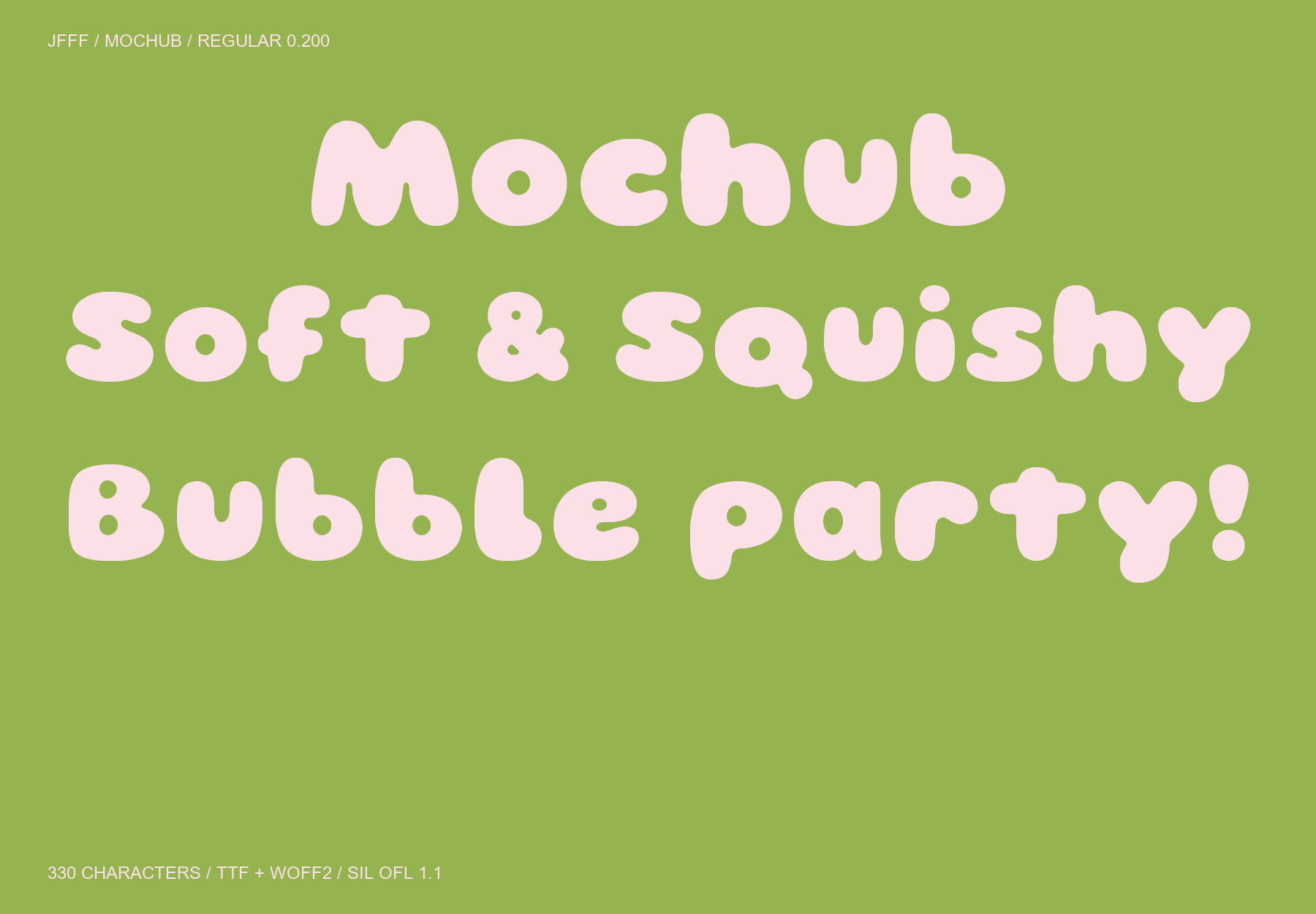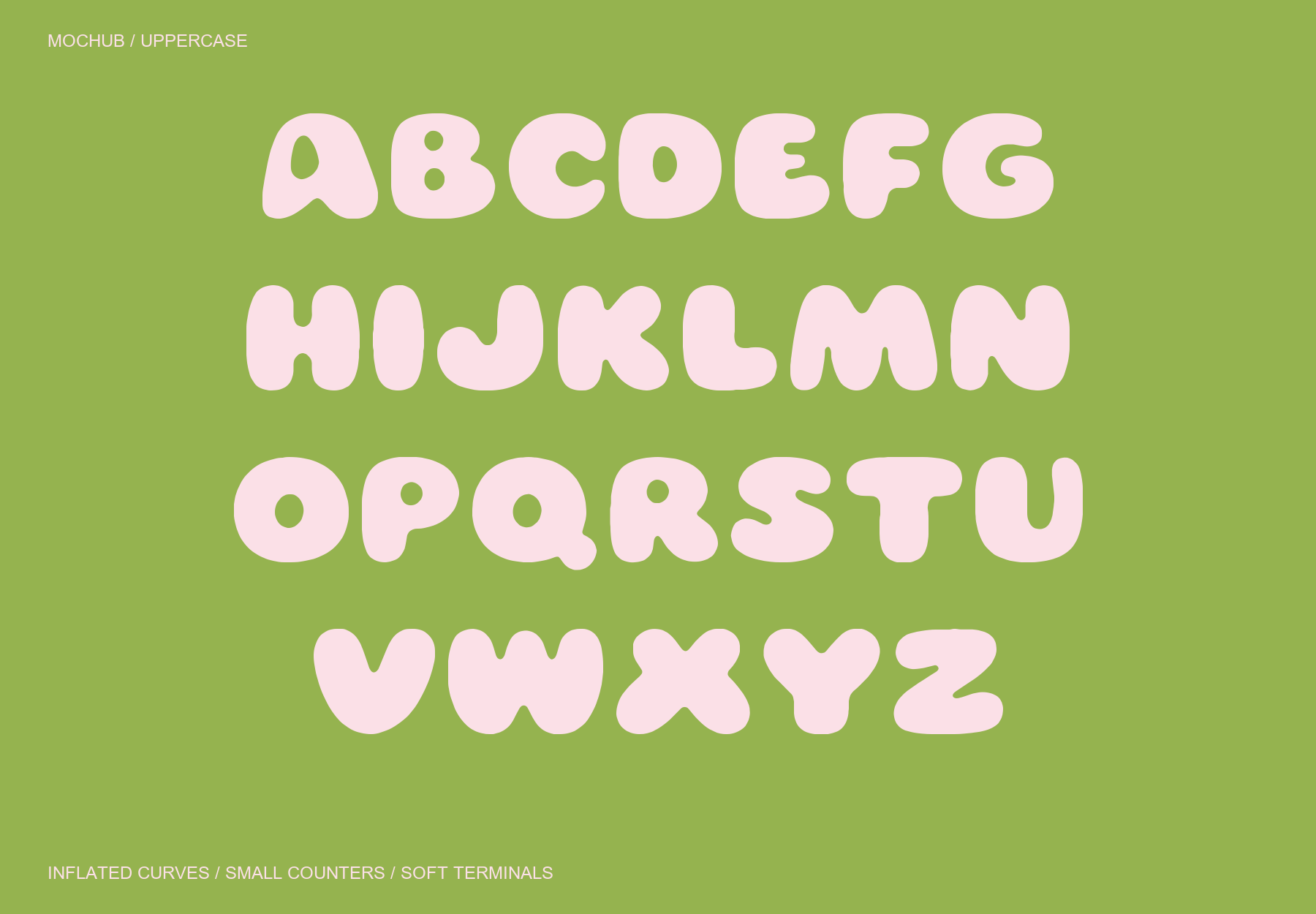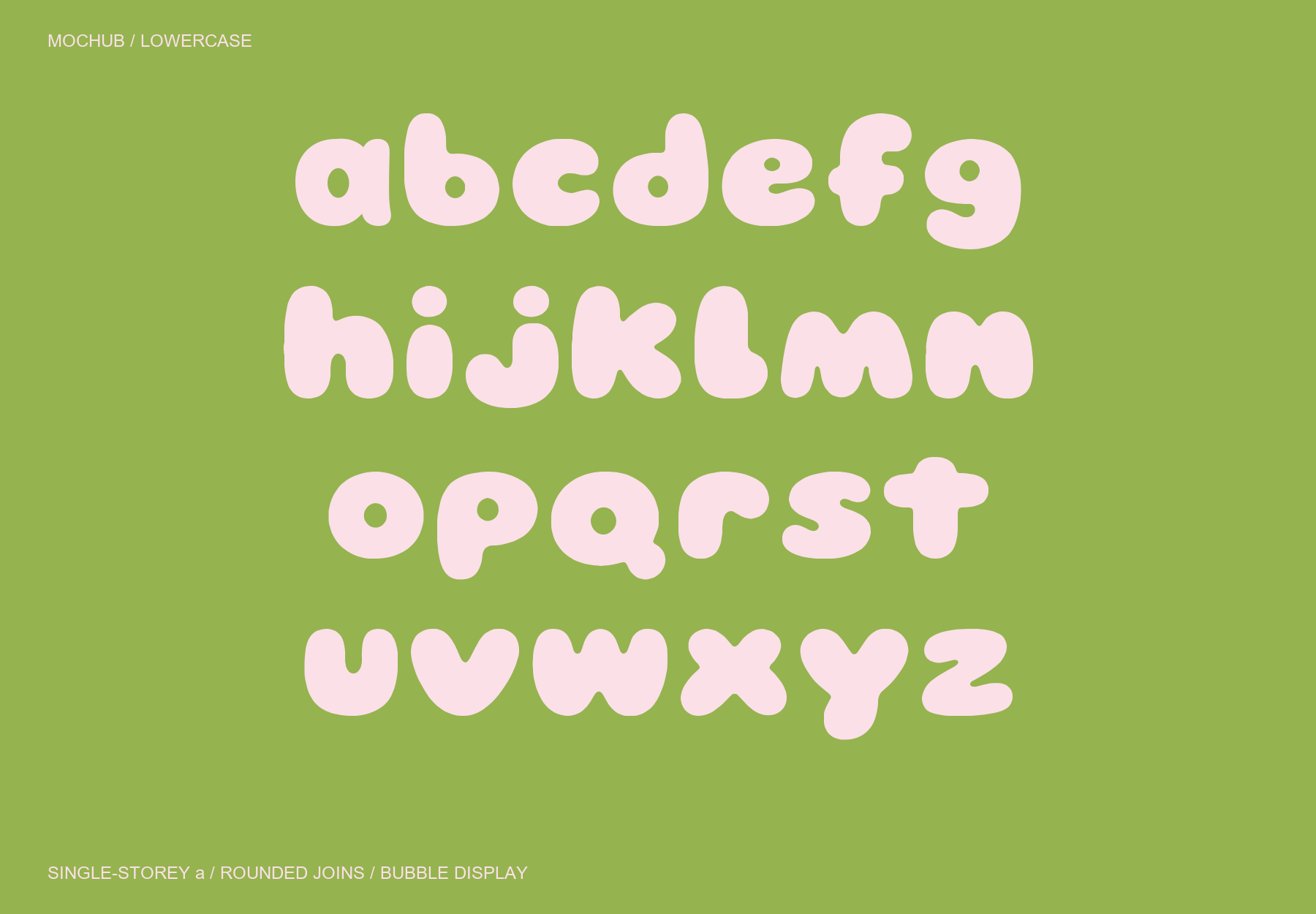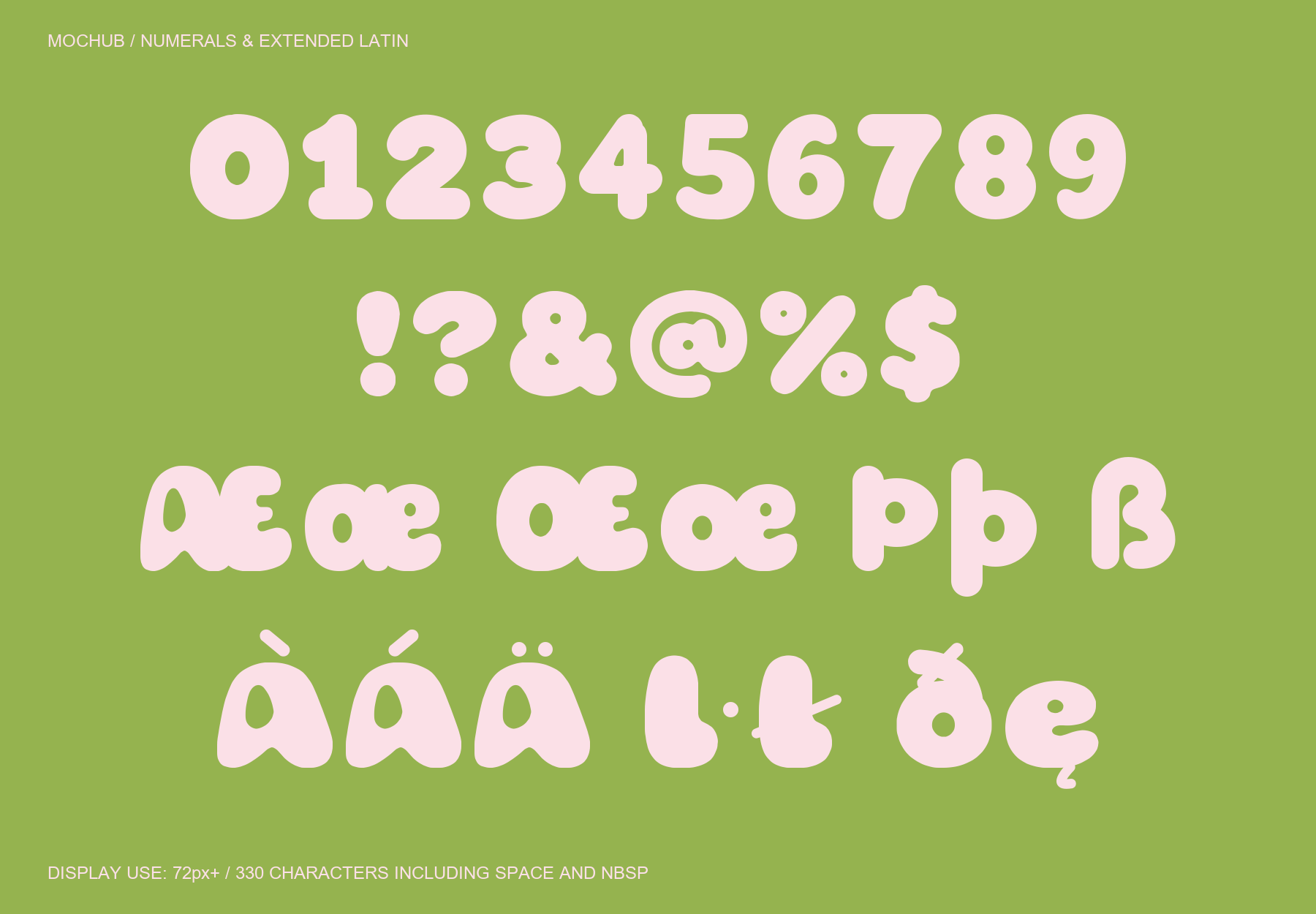
Mochub은 풍선처럼 부푼 획, 작은 속공간과 말랑하게 파인 연결부가 특징인 둥근 디스플레이 서체입니다. 소문자 a는 둥근 몸통과 짧은 오른쪽 기둥을 연결한 단층 구조로 설계했습니다. Regular 0.200 · 라틴 330자(공백·NBSP 2자 포함). 영문 대소문자, 숫자, 확장 라틴 악센트와 기호를 지원합니다. 한글은 포함하지 않으며 악센트는 완성형 문자로 지원합니다. TTF와 WOFF2를 하나의 ZIP으로 제공하고 SIL Open Font License 1.1로 무료 배포합니다. 72px 이상 제목·포스터·패키지에 권장합니다. 작은 본문에서는 작은 속공간의 가독성이 낮아질 수 있습니다. 330자를 17장으로 확대 검수하고 숫자 5, 따옴표, 밑줄, 통화기호와 확장 문자를 수정했습니다. 기본 12개 조합에서 악센트 파생 조합을 포함한 285쌍의 커닝을 적용했습니다. 108,900개 인접 조합의 경계 검사에서 겹침이 발견되지 않았습니다. 모든 조합을 수작업으로 커닝했다는 의미는 아닙니다. Windows 출력과 Edge·Chrome 웹폰트 로딩 및 커닝을 확인했습니다. macOS·Safari와 Adobe·Office 앱 UI는 미검수입니다.